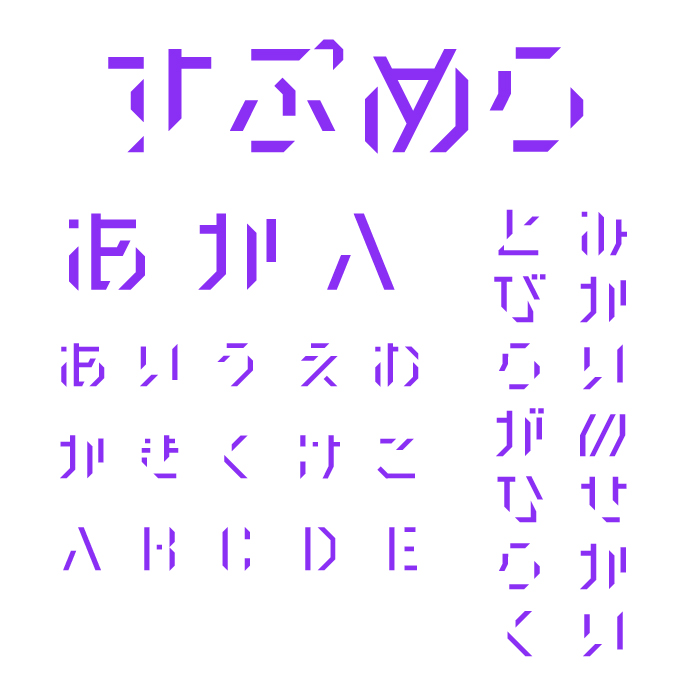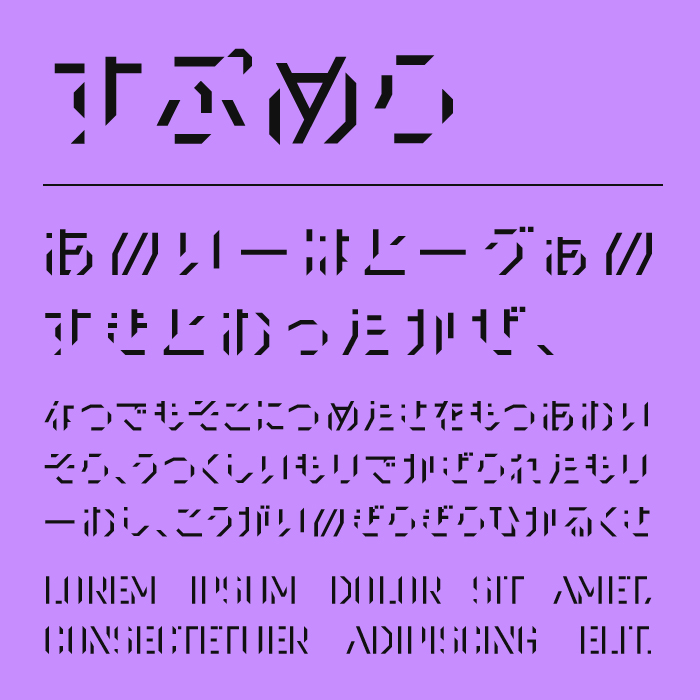
すぷめらフォントは、切り抜いたような細かい隙間が文字内に散りばめられた、非常に個性的なステンシル風デザインフォントです。
視覚的に分断されているにも関わらずきちんと読めるようにデザインされいます。
サイバーパンク、ハッキング、ノイズといったSFっぽいテーマと親和性が高く、タイトルロゴに仕上がるフォントです。
収録文字は、漢字・ひらがな・カタカナ・アルファベット・数字・記号が収録。